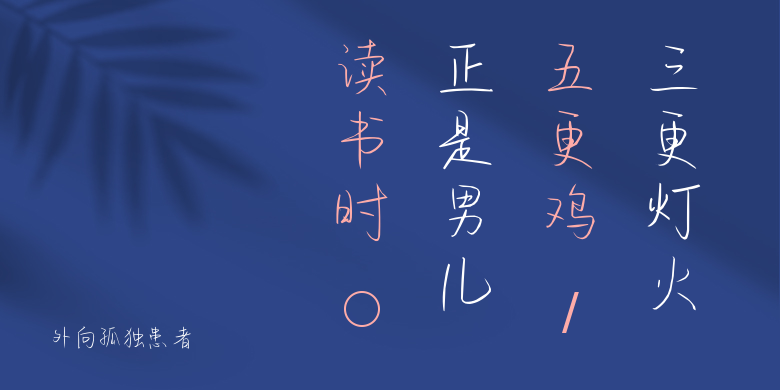
外向孤独患者
外向孤独患者,这款字体结构工整、笔画清晰,兼顾美观与易读性,适用于标题、正文、海报、包装、LOGO 等多种场景。字形优雅稳定,风格百搭耐看,适配日常排版与创意设计,让文字呈现更舒适、更具质感。外向孤独患者一笔一画,皆是细节,以均衡的比例、流畅的线条打造舒适视觉体验,字形端正大气,风格简约现代。无论是商业设计、品牌宣传还是日常排版,都能轻松驾驭,让文字更有格调与力量。外向孤独患者字体下载。